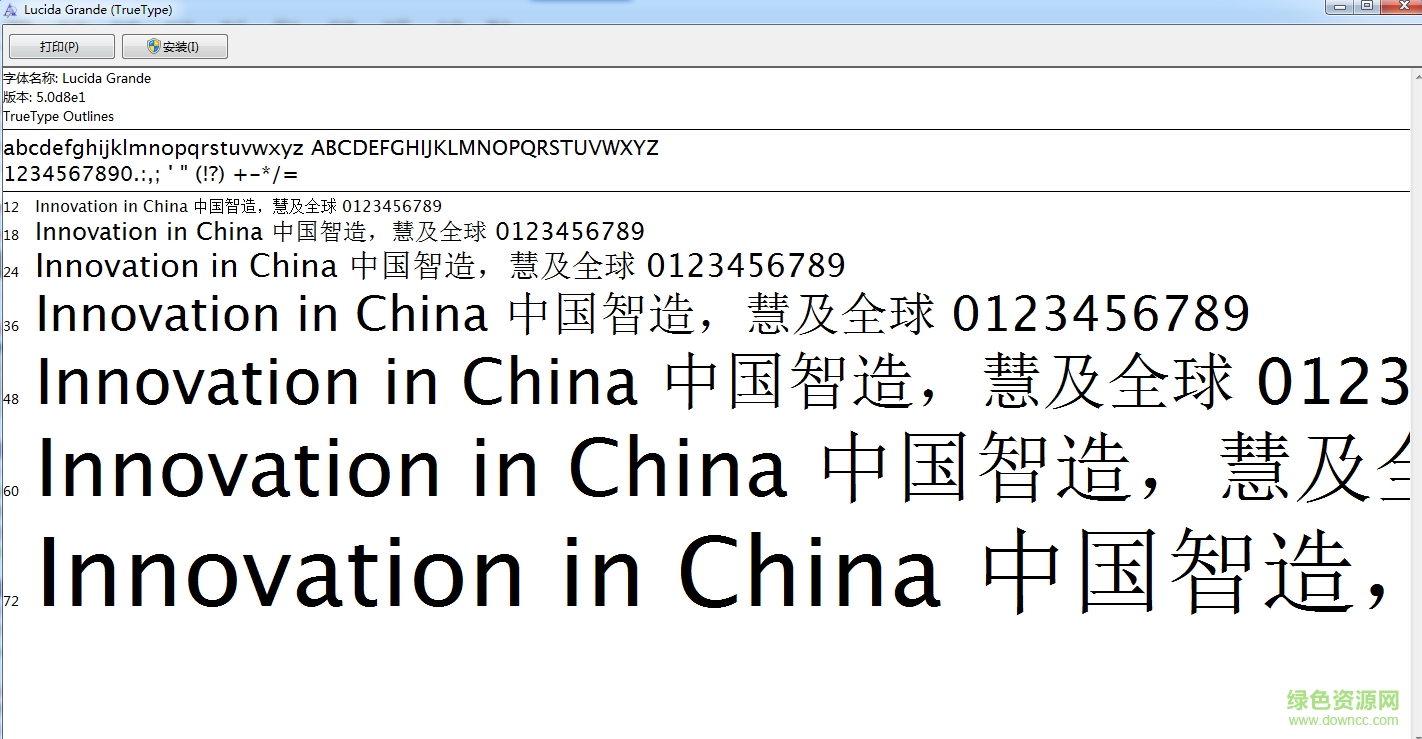
lucida grande是什么字體?lucida grande是ios操作系統(tǒng)以前的默認(rèn)字體,不過現(xiàn)在已經(jīng)換了,這款字體字形精美,結(jié)構(gòu)勻稱,用在網(wǎng)站設(shè)計(jì)或廣告方面效果都挺好,需要的朋友快來綠色資源網(wǎng)下載吧!
Lucida Grande是一種西文無襯線字體,是蘋果公司操作系統(tǒng) Mac OS X 9 以及之前版本的系統(tǒng)默認(rèn)西文字體。
它的設(shè)計(jì)師是查爾斯·畢格羅(Charles Bigelow)和克里斯·霍爾姆斯(Kris Holmes),是Lucida字體家族的一員,采用蘋果與微軟共同制定的TrueType標(biāo)準(zhǔn),拓展名為.ttf。
Lucida Grande支持Unicode2.0版本中大多數(shù)常用字符。